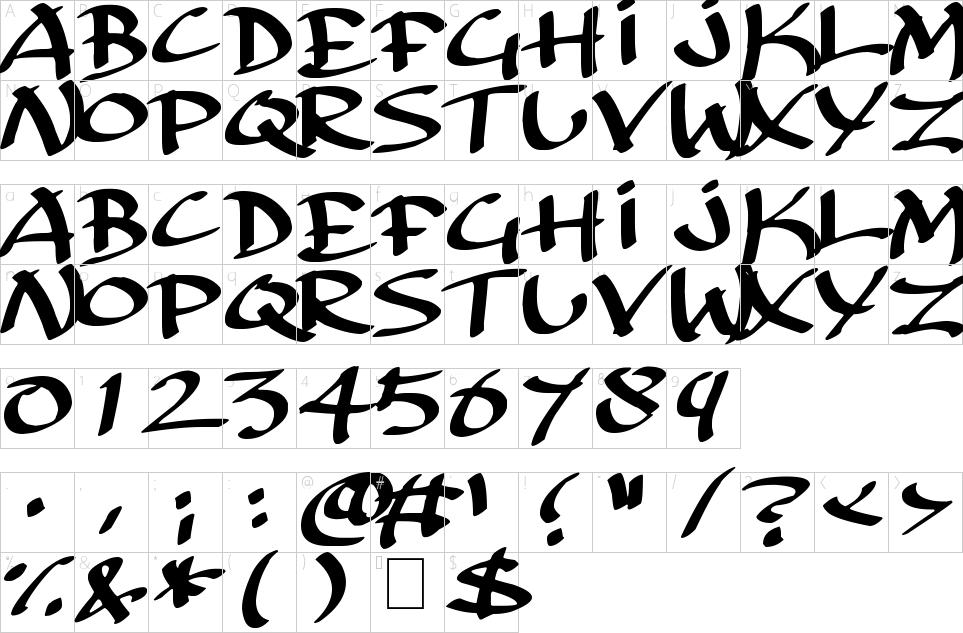
Descubra Archaic Asian Inks, uma fonte inovadora e única para quem busca algo diferente e envolvente. Este sistema de escrita não é apenas uma escolha para sua próxima obra de arte digital, mas também uma janela para uma cultura que se expressa através de linhas e traços. Archaic Asian Inks foi criada por Darrell Flood e já foi baixada milhares de vezes. Com seu design elegante e detalhado, é perfeito para criar logotipos, publicações de arte digital ou qualquer projeto que você queira expressar de uma maneira única. Esta fonte gráfica oferece uma combinação de elegância e criatividade que certamente vai agradar designers de todos os níveis. Download Archaic Asian Inks e transforme a forma como você visualiza design.